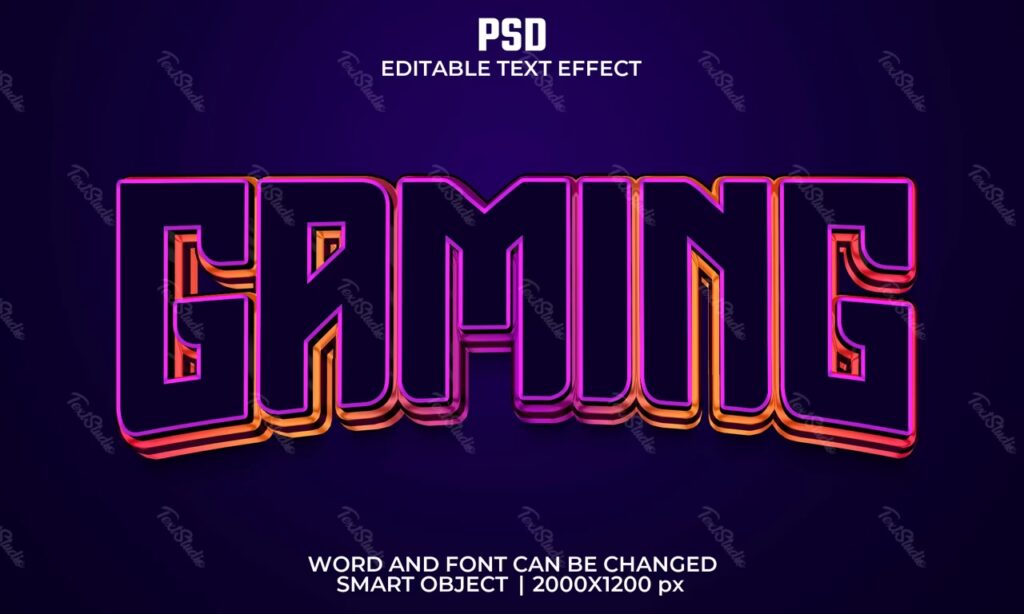
I computerspillets rige univers er hvert element designet til at trække spilleren dybere ind i oplevelsen. Fra grafik og lyd til gameplay-mekanikker spiller selv de tilsyneladende små detaljer en afgørende rolle. En af disse ofte oversete, men utroligt vigtige, detaljer er skrifttypen – den font, der bruges til titler, menuer, dialogbokse og alt tekst på skærmen. Valget af font kan alene formidle genre, stemning og brandidentitet. En dyster fantasy-font vil øjeblikkeligt sætte en anden tone end en futuristisk sci-fi-font eller en robust militærfont.
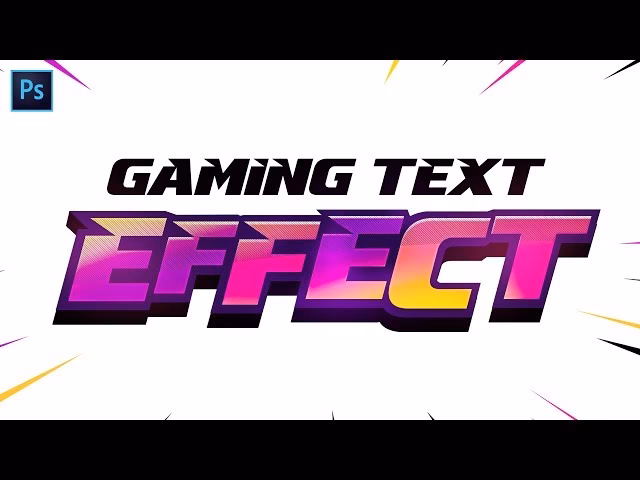
Spiludviklere lægger enormt meget arbejde i at vælge eller skabe den perfekte skrifttype, der komplementerer spillets æstetik og narrative. En god spilfont skal ikke kun se godt ud; den skal også være letlæselig under forskellige forhold, selv på små skærme eller i hektiske spilsituationer. Der findes ikke én enkelt 'videospilfont', da variationen er lige så stor som variationen i spilgenrer. Dog er der visse karakteristika, der ofte går igen i fonts, der bruges i spil, såsom dristighed, blokagtige former, futuristiske eller stiliserede udseender, der afspejler spillets tema.
Hvad Kendertegner en Typisk Spilfont?
Når man tænker på fonts i spil, dukker der ofte billeder op af skrifttyper, der er mere end bare tekst; de er en del af grafikken. Mange spil bruger fonts, der er specialdesignet til formålet for at sikre en unik visuel identitet. Andre bruger modificerede versioner af eksisterende kommercielle fonts. Fælles for mange af dem er, at de ofte er:
- Dristige og iøjnefaldende: De skal fange opmærksomhed, især i titler og overskrifter.
- Tematiske: De afspejler spillets genre – gotiske for fantasy, teknologiske for sci-fi, grove for action/adventure.
- Læsbarhed: Trods stilistiske valg skal teksten kunne læses hurtigt og nemt, især i menuer og UI-elementer.
- Unikke: Mange franchises stræber efter en font, der er umiddelbart genkendelig og forbundet med netop deres brand.
Dette behov for unikhed og tematisk relevans fører ofte til udviklingen af proprietære skrifttyper.
Call of Dutys Skrifttype: Mød Hitmarker
Et fremragende eksempel på en franchise med sin egen dedikerede skrifttype er den enormt populære Call of Duty-serie. Ifølge information er Call of Dutys officielle skrifttype kendt som Hitmarker. Navnet i sig selv vækker associationer til spillet, hvor et 'hitmarker' visuelt indikerer, at man har ramt en fjende.
Hitmarker er designet specifikt til Call of Duty-universet. Den beskrives som værende rodfæstet i klassisk militær terminologi – stor, fed og blokagtig. Disse karakteristika passer perfekt til spilseriens temaer om krig, kamp og robusthed. Samtidig er den bygget med moderne typografiske principper, hvilket sandsynligvis betyder, at den er optimeret for digital visning og forskellige anvendelser inden for franchisen.
Brugen af Hitmarker er en fundamental del af Call of Dutys visuelle identitet. Den sikrer konsistens på tværs af alle seriens aktiver, komponenter, IP'er (Intellectual Properties) og indhold. Uanset om det er på spilcoveret, i menuerne, på hjemmesiden eller i marketingmateriale, bidrager Hitmarker til øjeblikkeligt at identificere indholdet som værende en del af Call of Duty-familien. Dette viser tydeligt, hvor vigtigt valget af en dedikeret skrifttype kan være for et stort brand.
Hvad med Playstation og Andre Spil?
Du spurgte specifikt til skrifttypen, der ligner Playstation. Det er et godt spørgsmål, da Playstation-brandet også har en meget stærk visuel identitet. PlayStation har gennem tiden brugt forskellige fonts til sit logo og i sine systemer. Det ikoniske 'PS' logo har en meget specifik, stiliseret skrifttype. Til system-UI og marketingmaterialer har de brugt forskellige skrifttyper, herunder en modificeret version af Trade Gothic (især i PS3/PS4-æraen) og muligvis andre proprietære fonts til PS5. Informationen, jeg har til rådighed, specificerer dog ikke den præcise skrifttype, der aktuelt eller historisk er brugt i PlayStation-UI eller logoet, udover at det er en font, der ofte er forbundet med brandet.
Dette understreger et vigtigt punkt: Mange store spilfirmaer og konsolproducenter bruger enten stærkt modificerede kommercielle fonts eller skaber helt nye, proprietære fonts. Disse fonts er ofte ikke frit tilgængelige for offentligheden. Der findes dog mange kommercielle fonts, der er designet til at efterligne stilen af populære spilfonts, eller som passer godt til en gaming-æstetik.
At arbejde med tekst, især i et designmæssigt øjemed som i spil eller relateret materiale, handler ikke kun om at vælge en font. Det handler også om, hvordan teksten præsenteres visuelt – dens farve, størrelse, placering og effekter. Her kommer værktøjer til tekstvisualisering ind i billedet. Et eksempel på et sådant værktøj, baseret på den givne information, er en 'Image Generator'.
En 'Image Generator' service beskrives som et værktøj, der giver brugeren mulighed for at tilpasse og visualisere tekster. Kernen i et sådant værktøj er evnen til at finjustere en række visuelle parametre: